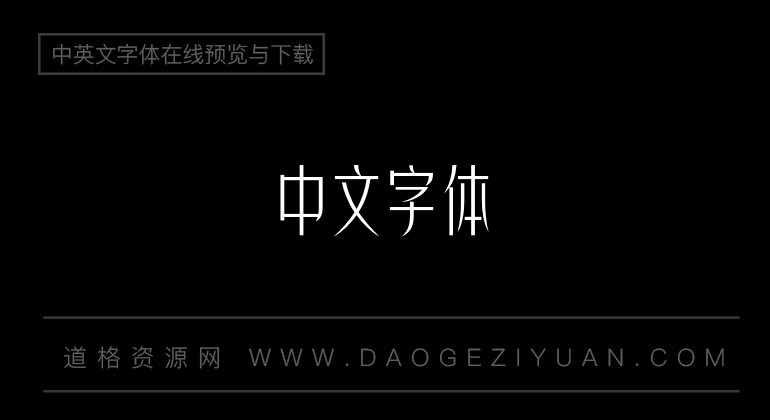
方正非凡体简体
方正非凡体简体字体是由方正字库设计的一款简约大气的字体,它拥有极佳的可读性、良好的空间感及良好的细节设计,具有超强的表现力和清晰的表达力。字体的设计重点是以清新大方的空间感为主,以细节的处理和精致的表现力为辅,极大地提升了文字的表现力,使文字更加易读、易记。
方正非凡体简体是一款非常不错的手写艺术字体,具有很好的视觉感,适合于文化类的宣传设计、商业类品牌的广告和产品包装设计以及个性化文字排版等较多场景。